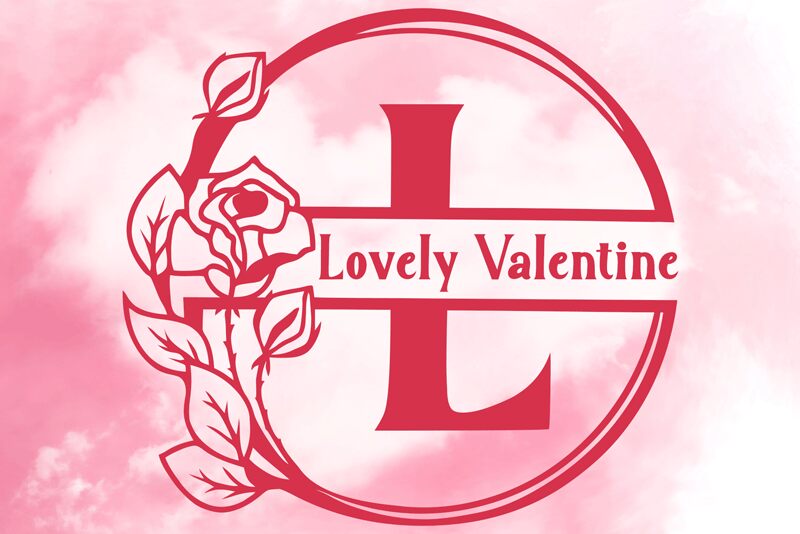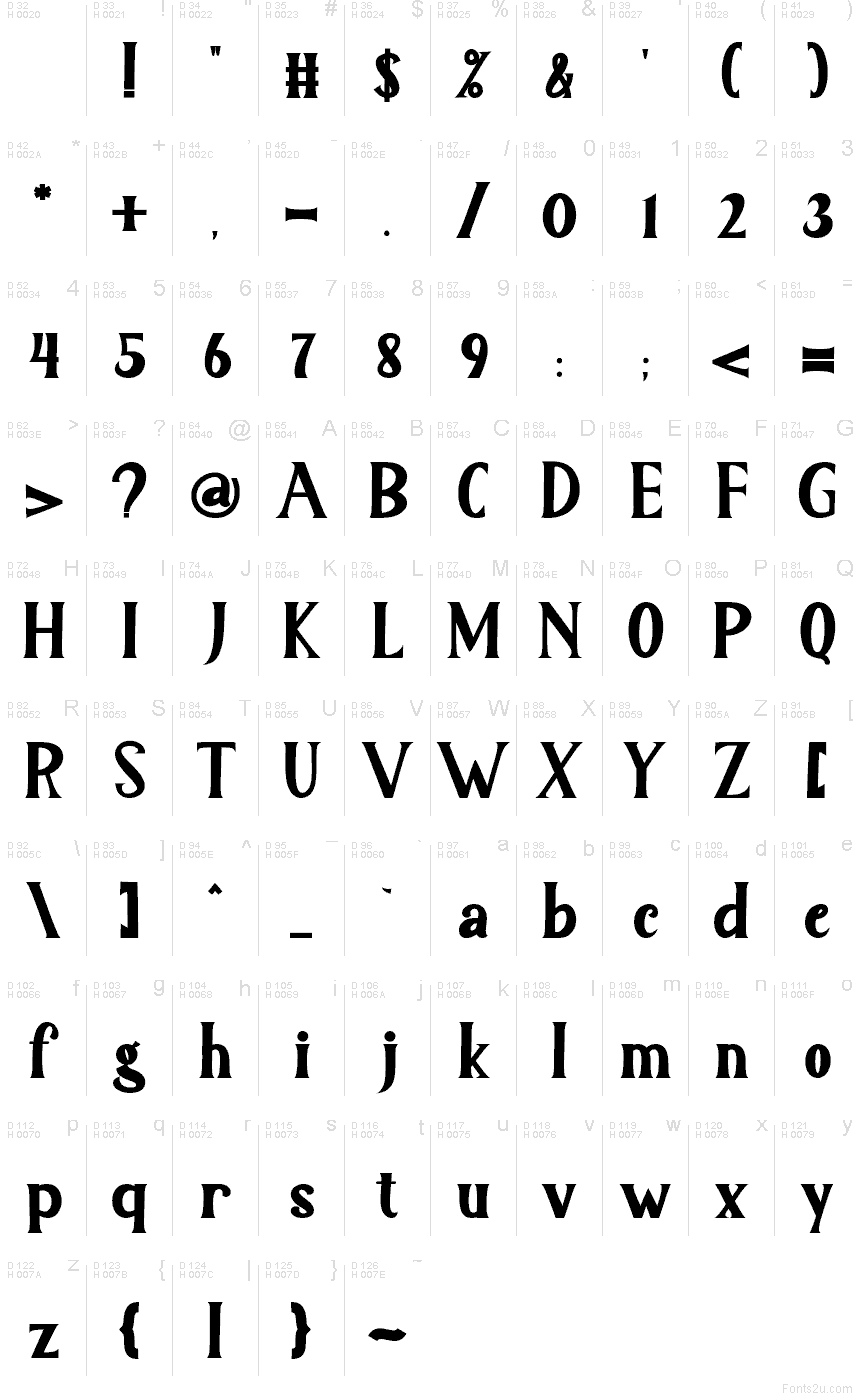
Lovely Valentine Monogram
Lovely Valentine Monogram de Yoga Letter es una tipografía gratuita de estilo display ideal para San Valentín, con formas serifadas y un ritmo decorativo de alto contraste. Sus formas redondeadas y detalles de acabado afilado le dan un aire formal de tarjeta de felicitación sin perder ese toque hecho a mano.
Lovely Valentine Monogram funciona muy bien en invitaciones de boda, tarjetas de San Valentín, etiquetas de regalo, detalles de logotipos, gráficos para redes sociales y packaging de boutiques. Esta tipografía gratuita es perfecta para textos cortos de temporada y diseños tipo monograma, ya que sus letras tienen suficiente carácter para enmarcar fácilmente nombres, títulos y pequeños mensajes decorativos.